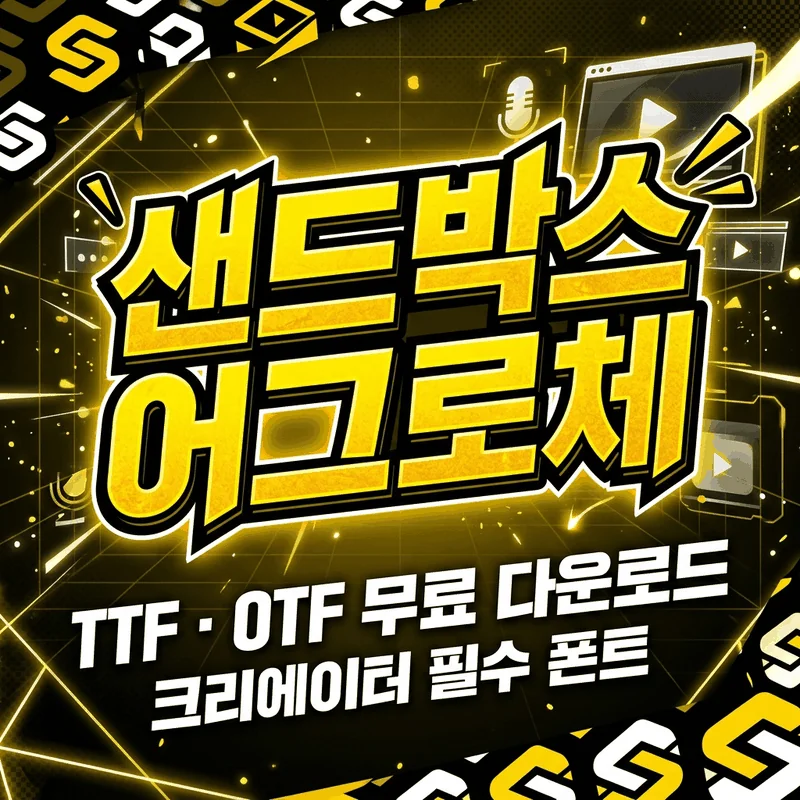
์œ ํŠœ๋ธŒ ์ธ๋„ค์ผ ํ•˜๋‚˜ ๋งŒ๋“ค ๋•Œ๋„, ํฌ์Šคํ„ฐ ํƒ€์ดํ‹€ ํ•˜๋‚˜ ์žก์„ ๋•Œ๋„ ํฐํŠธ ์„ ํƒ์ด ์ „์ฒด ๋ถ„์œ„๊ธฐ๋ฅผ ์ขŒ์šฐํ•ฉ๋‹ˆ๋‹ค. ์ €๋Š” ์œ ํŠœ๋ธŒ ์ธ๋„ค์ผ๊ณผ ๋ฐฐ๋„ˆ ์ž‘์—…์„ ํ•  ๋•Œ๋งˆ๋‹ค "๊ฐ•๋ ฌํ•˜๋ฉด์„œ๋„ ์„ธ๋ จ๋œ ํฐํŠธ"๋ฅผ ์ฐพ๋‹ค๊ฐ€ ๊ฒฐ๊ตญ ๋Š˜ ์ƒŒ๋“œ๋ฐ•์Šค ์–ด๊ทธ๋กœ์ฒด๋กœ ๋Œ์•„์˜ค๊ฒŒ ๋ฉ๋‹ˆ๋‹ค.
1. ์–ด๊ทธ๋กœ์ฒด๋ž€? ํƒ„์ƒ ๋ฐฐ๊ฒฝ ๐Ÿ›๏ธ
์–ด๊ทธ๋กœ์ฒด๋Š” ๊ตญ๋‚ด ๋Œ€ํ‘œ MCN ๊ธฐ์—… (์ฃผ)์ƒŒ๋“œ๋ฐ•์Šค๋„คํŠธ์›Œํฌ๊ฐ€ ๊ฐœ๋ฐœํ•ด ๋ฌด๋ฃŒ๋กœ ๋ฐฐํฌํ•œ ์„œ์ฒด์ž…๋‹ˆ๋‹ค. 2021๋…„ 8์›”, "๋” ๋งŽ์€ ํฌ๋ฆฌ์—์ดํ„ฐ๋“ค์˜ ์ฐฝ์ž‘ ํ™œ๋™์„ ์‘์›ํ•œ๋‹ค"๋Š” ๋ฉ”์‹œ์ง€๋ฅผ ๋‹ด์•„ ์ƒŒ๋“œ๋ฐ•์Šค ์ตœ์ดˆ์˜ ๋ธŒ๋žœ๋“œ ํฐํŠธ๋กœ ๊ณต๊ฐœ๋˜์—ˆ์Šต๋‹ˆ๋‹ค.
ํฌ๋ฆฌ์—์ดํ„ฐ๋ฅผ ์œ„ํ•ด ๋งŒ๋“ค์–ด์ง„ ํฐํŠธ๋‹ต๊ฒŒ, ๊ตฌ์กฐ ์ž์ฒด๊ฐ€ ์˜์ƒ ์ธ๋„ค์ผ๊ณผ ํƒ€์ดํ‹€ ๋””์ž์ธ์—์„œ ๊ฐ€์žฅ ๋ˆˆ์— ๋„๋„๋ก ์ตœ์ ํ™”๋˜์–ด ์žˆ๋Š” ๊ฒƒ์ด ํŠน์ง•์ž…๋‹ˆ๋‹ค.
2. ์–ด๊ทธ๋กœ์ฒด์˜ 3๊ฐ€์ง€ ํ•ต์‹ฌ ํŠน์ง• ๐Ÿ”
โ‘  ๋…ํŠนํ•œ ๊ณก์„  + ์‚ฌ์„ ์˜ ์กฐํ•ฉ
์–ด๊ทธ๋กœ์ฒด์˜ ๊ฐ€์žฅ ํฐ ์‹œ๊ฐ์  ํŠน์ง•์€ ํš์˜ ์‹œ์ž‘๊ณผ ๋์— ๋“ค์–ด๊ฐ„ ๋‹ค์–‘ํ•œ ๊ฐ๋„์˜ ์‚ฌ์„  ์ฒ˜๋ฆฌ์ž…๋‹ˆ๋‹ค. ๊ธ€์ž๋งˆ๋‹ค ๋†’์ด์™€ ํญ์— ๋ฏธ์„ธํ•œ ์ฐจ์ด๋ฅผ ๋‘์–ด ๊ณ„๋‹จ์‹ ๋ฆฌ๋“ฌ๊ฐ์„ ๋ถ€์—ฌํ–ˆ๊ธฐ ๋•Œ๋ฌธ์—, ์—ฌ๋Ÿฌ ๊ธ€์ž๊ฐ€ ๋ชจ์ด๋ฉด ์—๋„ˆ์ง€๊ฐ€ ๋„˜์น˜๋Š” ๊ฒƒ์ฒ˜๋Ÿผ ๋ณด์ž…๋‹ˆ๋‹ค.
โ‘ก 3๊ฐ€์ง€ ๊ตต๊ธฐ ์ง€์› (Light/Medium/Bold)
๋‹ค์–‘ํ•œ ์ƒํ™ฉ์— ๋งž์ถฐ ์„ ํƒ ๊ฐ€๋Šฅํ•œ 3๊ฐ€์ง€ ๊ตต๊ธฐ๋ฅผ ๊ธฐ๋ณธ ์ œ๊ณตํ•ฉ๋‹ˆ๋‹ค. ์ƒํ™ฉ๋ณ„ ์ถ”์ฒœ ์šฉ๋„๋Š” ๋‹ค์Œ๊ณผ ๊ฐ™์Šต๋‹ˆ๋‹ค.
• Light: ์‚ฐ๋œปํ•œ ๋ฐฐ๊ฒฝ ํ…์ŠคํŠธ, ์†Œ์ œ๋ชฉ์šฉ
• Medium: ๋ธ”๋กœ๊ทธ ํƒ€์ดํ‹€, ์นด๋“œ๋‰ด์Šค ๋ณธ๋ฌธ ๊ฐ•์กฐ์šฉ
• Bold: ์œ ํŠœ๋ธŒ ์ธ๋„ค์ผ, ๊ฐ•๋ ฅํ•œ ํƒ€์ดํ‹€ ํšจ๊ณผ์šฉ
โ‘ข ์™„๋ฒฝํ•œ ๊ธ€์ž ์ˆ˜ ์ง€์›
ํ•œ๊ธ€ 2,350์ž, ์˜๋ฌธ 94์ž, ์•ฝ๋ฌผ 300์ž๋ฅผ ์™„๋ฒฝํ•˜๊ฒŒ ์ง€์›ํ•ฉ๋‹ˆ๋‹ค. ์˜๋ฌธ ์˜๋ฌธ ์•ŒํŒŒ๋ฒณ์—๋„ ์–ด๊ทธ๋กœ์ฒด ํŠน์œ ์˜ ์Šคํƒ€์ผ์ด ๊ทธ๋Œ€๋กœ ๋…น์•„ ์žˆ์–ด ํ•œ์˜ ํ˜ผํ•ฉ ๋””์ž์ธ ์‹œ ํ†ต์ผ๊ฐ์ด ๋›ฐ์–ด๋‚ฉ๋‹ˆ๋‹ค.
6. ํ™œ์šฉ ํŒ ๋ฐ ๋งˆ๋ฌด๋ฆฌ ๐ŸŽจ
์ง์ ‘ ์‚ฌ์šฉํ•ด๋ณธ ๊ฒฐ๊ณผ, ์–ด๊ทธ๋กœ์ฒด๋Š” ์œ ํŠœ๋ธŒ ์ฑ„๋„ ์•„ํŠธ๋‚˜ SNS ์ƒ์„ธํŽ˜์ด์ง€ ํƒ€์ดํ‹€์—์„œ ๊ฐ€์žฅ ๊ฐ•๋ ฅํ•œ ์‹œ๊ฐ์  ์ž„ํŒฉํŠธ๋ฅผ ๋ณด์—ฌ์ค๋‹ˆ๋‹ค. ๋‹ค๋งŒ ์‚ฌ์„ ์ด ๋งŽ์ด ๋“ค์–ด๊ฐ„ ๋…ํŠนํ•œ ๊ตฌ์กฐ์ƒ, ๋ฒ•๋ฅ  ๋ฌธ์„œ๋‚˜ ๊ธˆ์œต ์•ˆ๋‚ด์ฒ˜๋Ÿผ ์ฐจ๋ถ„ํ•œ ์‹ ๋ขฐ๊ฐ์ด ํ•„์š”ํ•œ ๊ณณ์—” ๋‹ค์†Œ ๋งž์ง€ ์•Š์„ ์ˆ˜ ์žˆ์Šต๋‹ˆ๋‹ค.